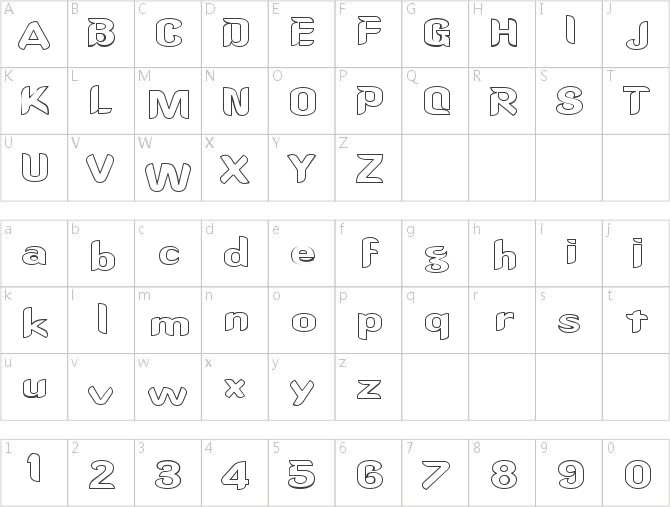
FZ HAND 15 HOLLOW EX
FZ HAND 15 HOLLOW EX介紹
FZ HAND 15 HOLLOW EX字體字庫是一款讓人賞心悅目、百看不厭的英文字體,適合各類廣告和產品包裝設計應用,字體大小0.03MB,格式為ttf字體,上傳用戶是15331803325,作者/版權方為未知